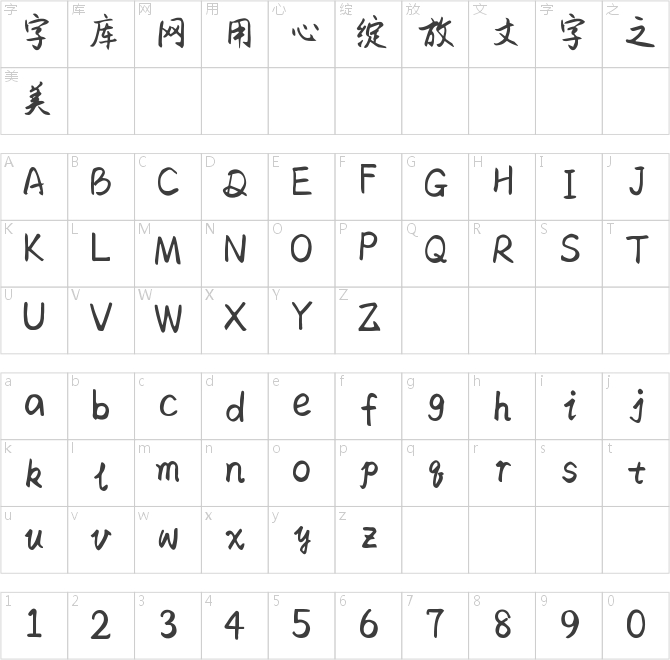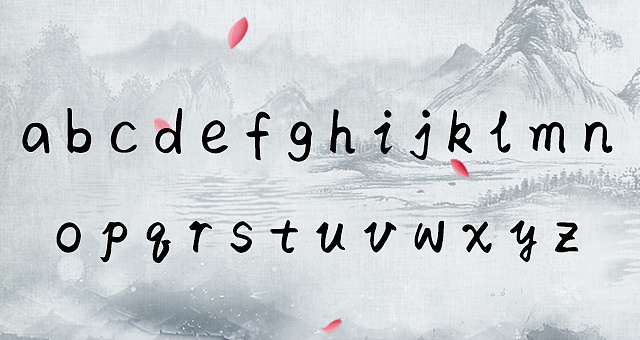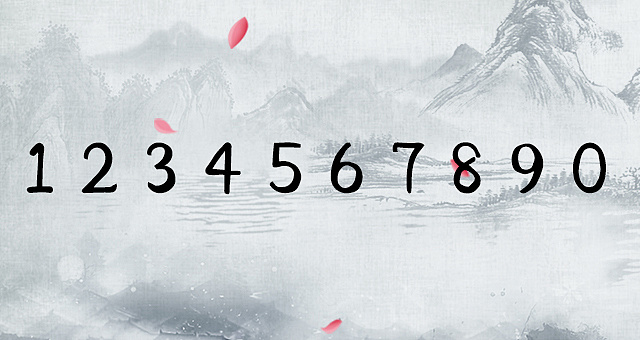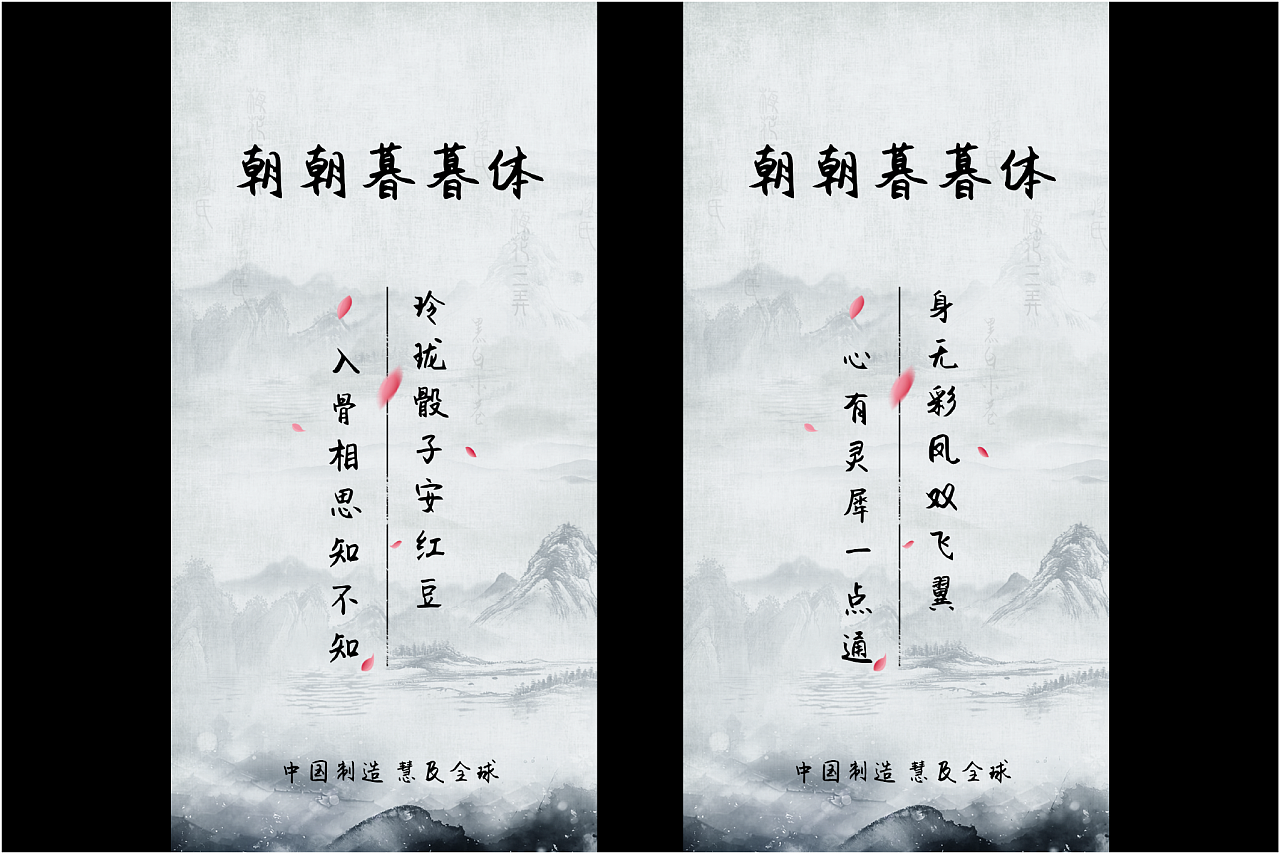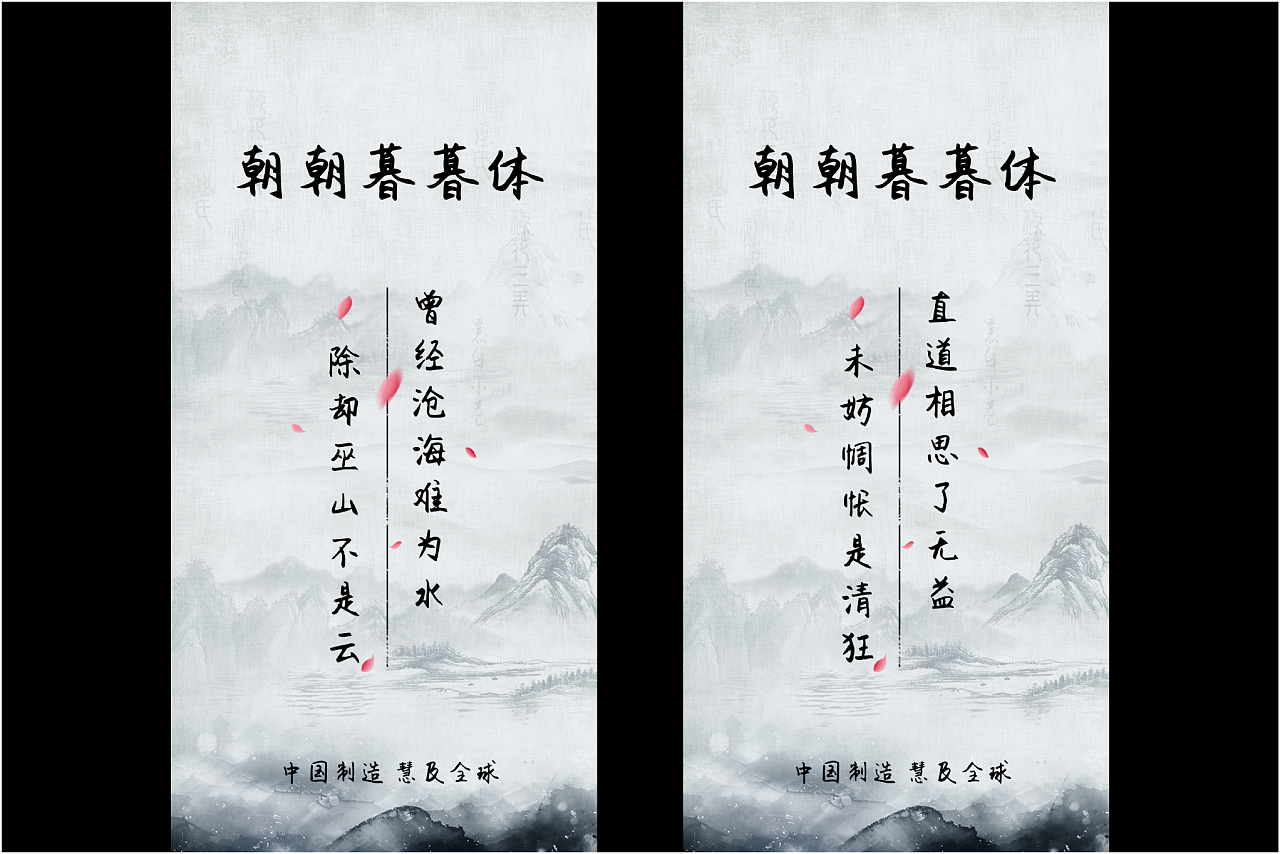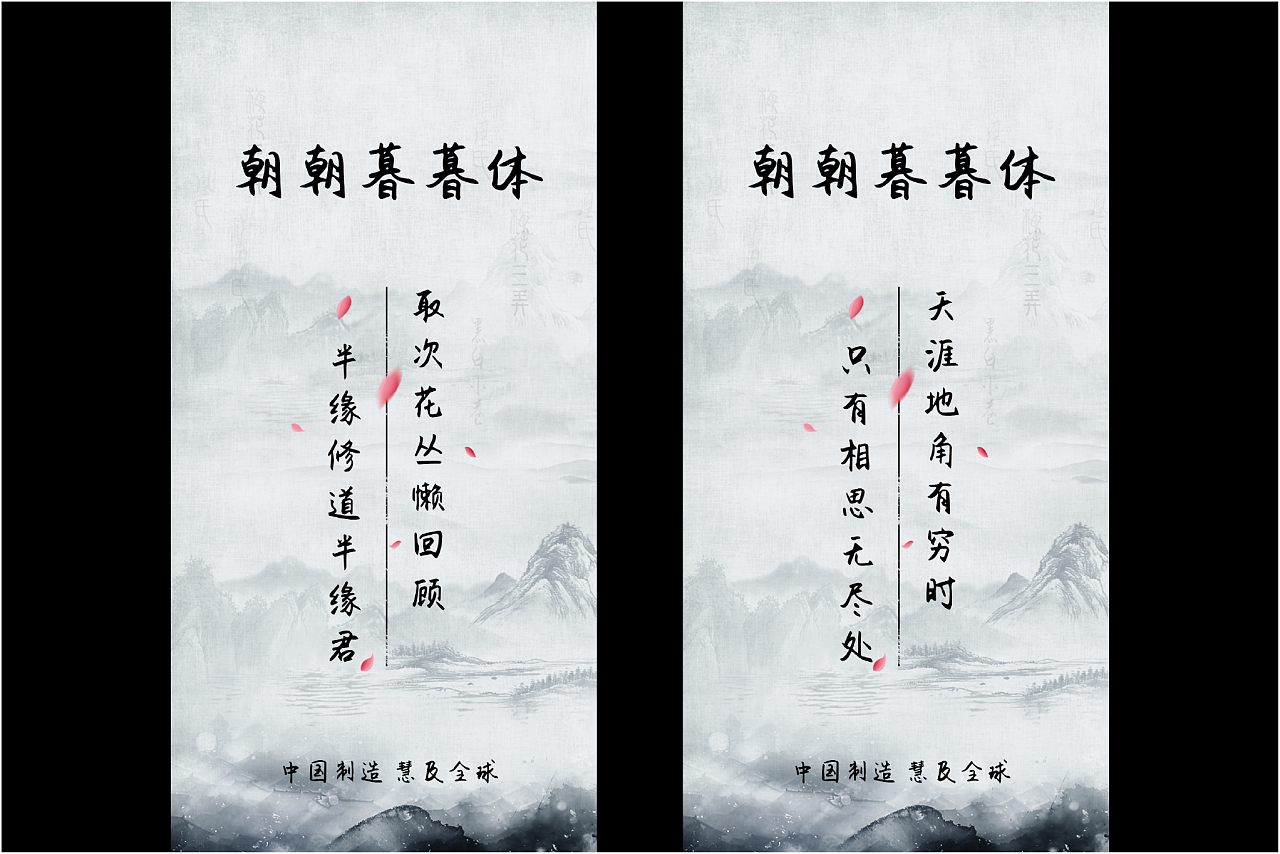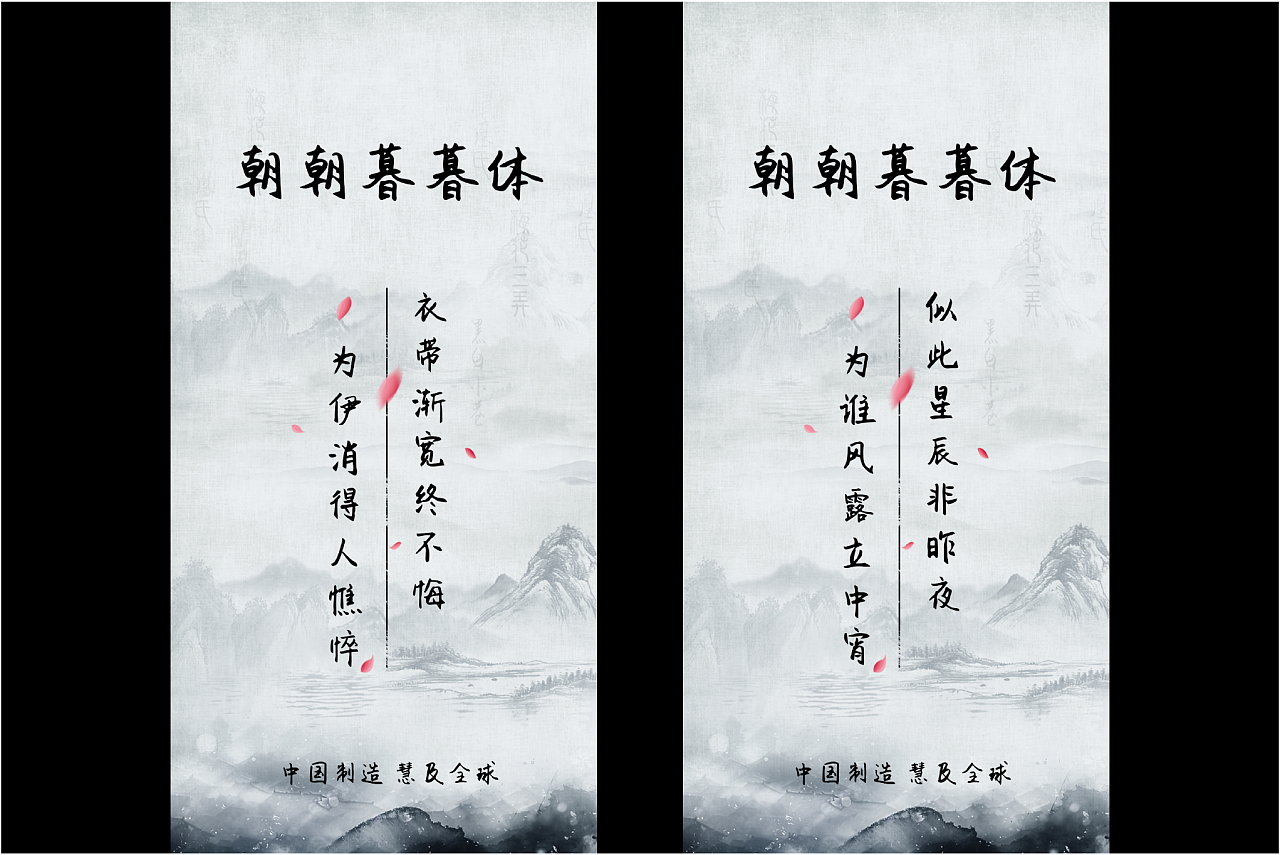
朝朝暮暮體 詳情頁
手寫字庫字體(含漢字6763個,符號字母若干)
朝朝暮暮體為毛筆書寫字體,字形寫意,結(jié)構(gòu)放松。適用于漫畫、書刊、品牌廣告和產(chǎn)品包裝設(shè)計,以及社交網(wǎng)絡(luò)的個性化用字。
字母和數(shù)字部分
字體字形應(yīng)用及展示